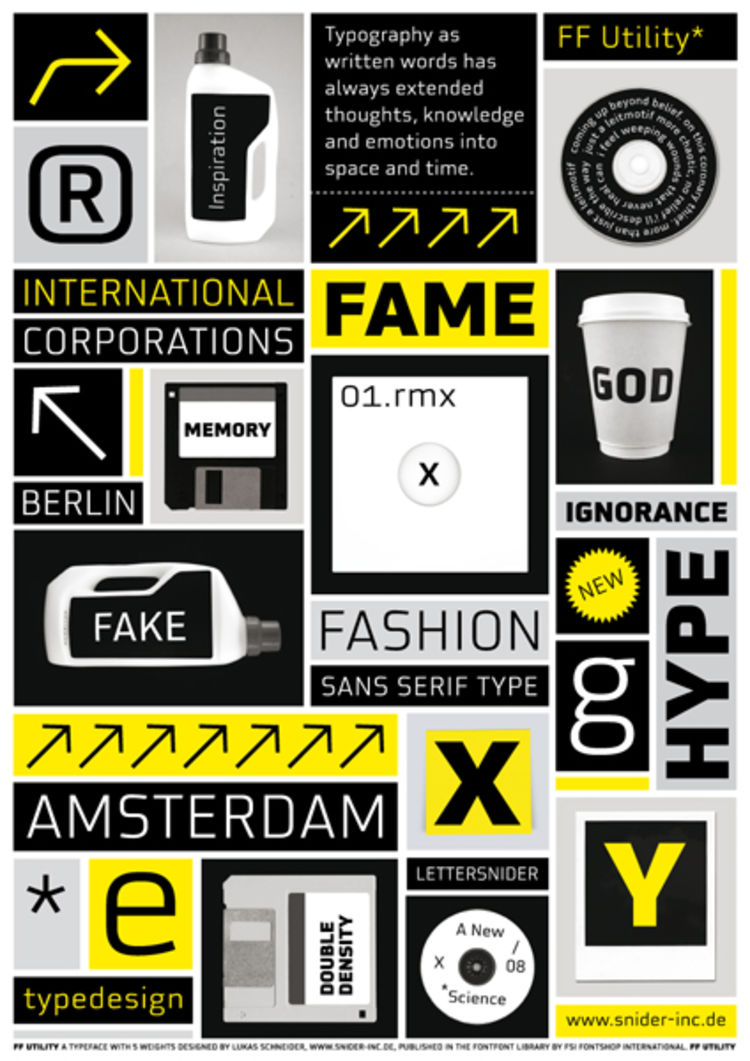
HfG-Absolvent Lukas Schneider entwickelte die serifenlose Schriftfamilie FF Utility, die nun bei FontShop erhältlich ist. Ursprünglich war FF Utility nur als Headlineschrift konzipiert, entwickelte sich aber während des Designprozesses immer mehr zu einer funktionalen Satzschrift. Die Grundlage der Schrift ist die Mischung aus Konstruktion und Freiform.
FF Utility entfernt sich von der konstruierten Anmutung und integriert humanistische Elemente. FF Utility beinhaltet 5 Schnitte, Proportional-Figures,Tabular-Figures, Oldstyle- und Odlstyle-Tabular-Figures, sowie Variationen des „g“ und „a“, die dem Anwender Spielraum bei der typografischen Gestaltung lassen.